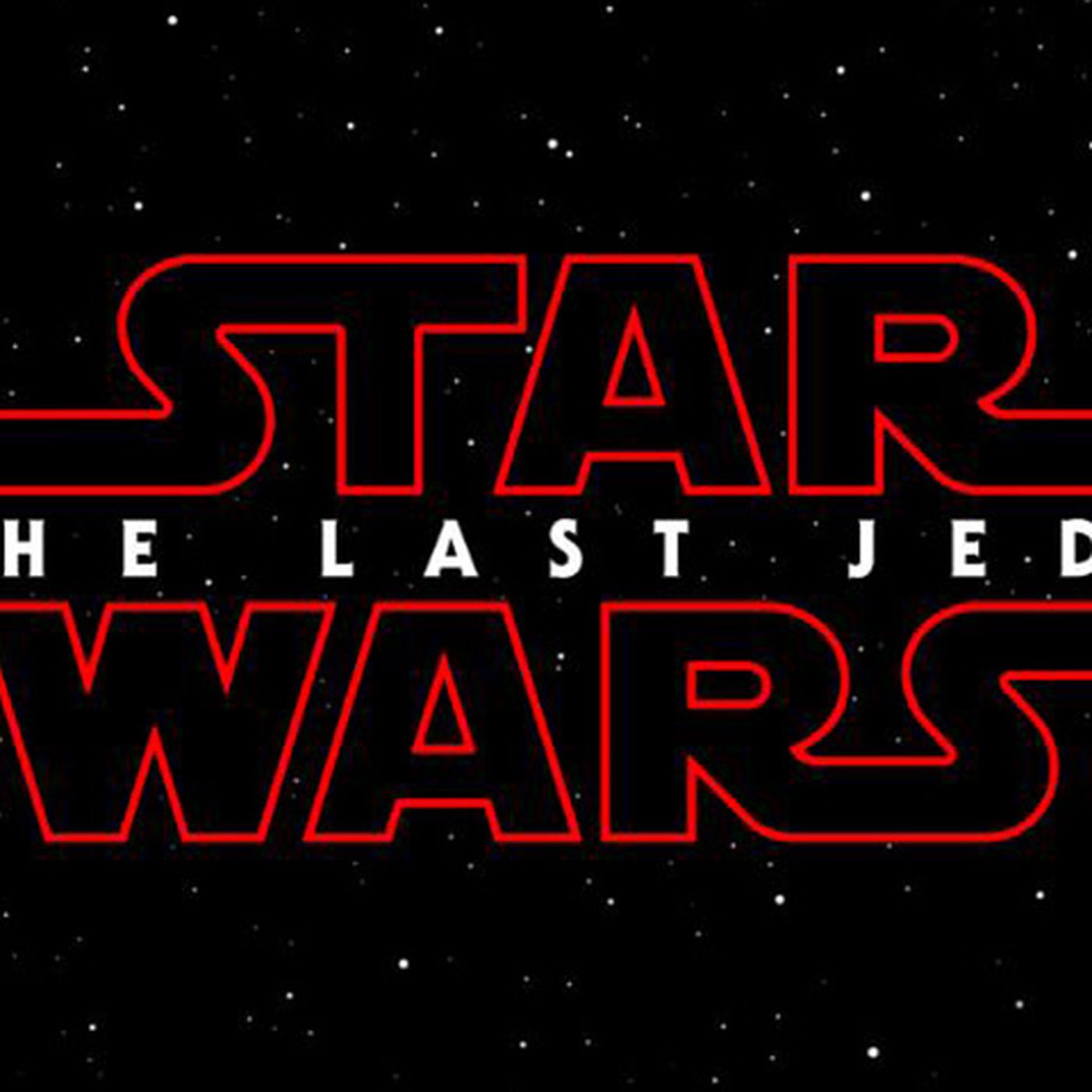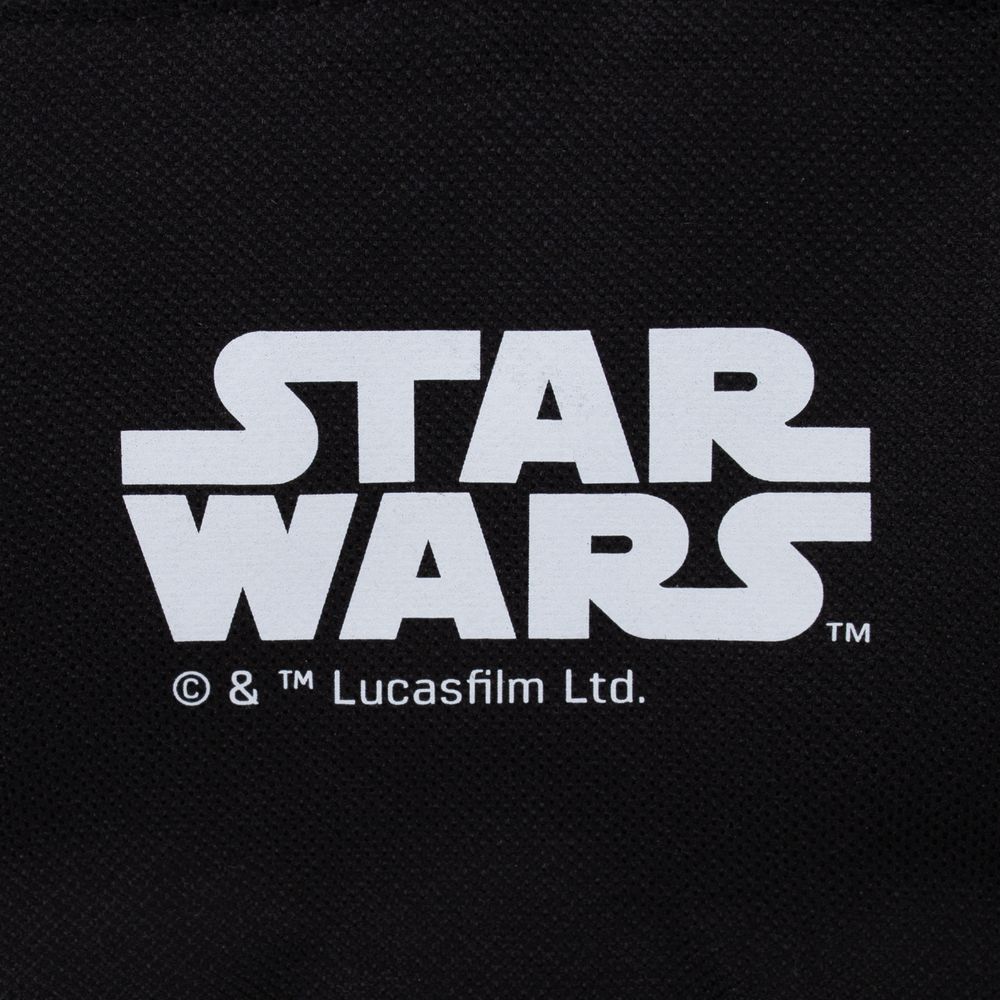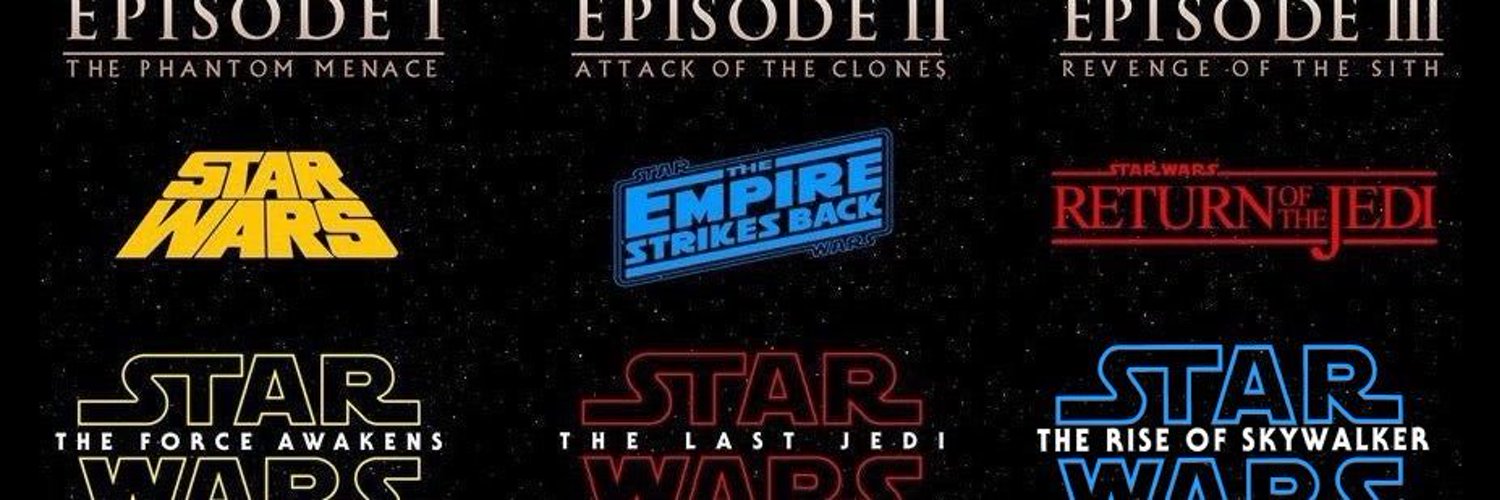
Звездные Войны Update: Новый шрифт, подкорректирован шаблон. Новый формат дат. (До битвы на явине) (после б.я) Империя Хатт Хатты — раса больших брюхоногих, которым присущи маленькие руки, широкий рот и огромные глаза. Они контролировали гигантскую космическую империю в Пространстве Хаттов. Хатты произошли с планеты Варл, но затем перебрались на Нал Хатту. Стоит что многие из хаттов были криминальными баронами. Взрослые хатты представляют собой тучных существ с общим весом тела около одной тонны. у хаттов довольно сильное сопротивление к обману разума через Силу благодаря природному иммунитету. Хатты могут видеть в ультрафиолетовом свете и других спектрах, невидимых для человеческого глаза.
Часто богатые хатты подсвечивали свои дворцы в спектрах такого рода, давая злоумышленникам ложное чувство скрытности. 25 тыс. дбя До создания Галактической империи, на внешних кольцах галактики, а так же на некоторых системах средних колец, появилась империя хаттов. Ее правление заняли главные кланы хаттов, называемые Кланами Древних. В период от заката Империи Раката, и до основания Республики, империя хаттов являлась основной и доминирующей силой. Ксим, также известный как Дарита Ксим и Ксим Деспот -человек,мужчина. В 20 лет разбоготел благодаря деньгам награбленным его отцом, Королём Пиратом Зера 8. Империя хаттов заключила союз с никто, клатуинцами и водранами, для битвы за планету Вонтор. После сражения победившие хатты и их союзники подписали Вонторский Договор, устанавливающий господство хаттов, над расами и всем звездным скоплением Си’Клаата, внешнего кольца галактики. После битвы, Ксим был предан, и брошен в тюрьму хаттов, где сгнил так и не увидев свободы.
Со временем Империя Хаттов развалилась, участвуя в постоянных локальных войнах. На рубеже зарождения Республики, агенты поспособствовали уничтожению ключевых фигур Хаттов. Оставшееся пространство после Империи, стало именоваться Пространством Хаттов, где в отдельных регионах правили отдельные кланы Хаттов. Гипердрайв .До времен республики, у многочисленных рас небыло своих гипердвигателей, и заменой служили различные технологические приспособления. У людей это были стазис камеры, позволяющие лететь в течении столетий без старения, или гиперпушки, которые в прямом смысле отстреливали корабли, позволяя им развить скорость равной скорости света, и тем самым образовать гипертунель. Чуть позже, после падения империи Раката, люди стали улучшать свои технологии, и вошли в число первых рас, кто создал собственный гипердвигатель, на основе ракатского. В их число вошли рогатые гуманоиды Деваронцы, с планеты Деварон, и Госсманы, похожих на маленьких динозавров существ, с планеты Кастелл.
Госсман Семена Республики В конце 25 тысячилетия дбя, почти через двести лет после падения империи раката, народы планет Кореллия и Дуро, наконец открыли способы работы с Силой, настроив двигатели раката, и на их основе создали более современную версию гипердрайва. В течении 20 лет, технология была стабилизирована для массового пользования и Коррелианцы стали продавать двигатели в ближайшие звездные системы. Позже и остальыне расы присоеденились к разработкам двигателя, тем самым последующие тысячилетия двигатель изменялся и усовершенствовался в зависимости от потребностей той или иной расы. Это время было названа Эпохой Экспансии. Много новых рас покидало свои родные миры, и отправлялись исследовать новые звезды. Торговые отношения в центральном секторе галактики, зародили первые семена будующей Галактической Республики. зг< Charge planes зз Effect channels 34 Inter-level conduits 35 Core chamber holds generator Пример строения Гипердрайва. Рождение Республики состоялось при подписании Галактической Конституции в 25053 ДБЯ во время Объединительных войн.
В тот период люди и дуросы, изучив технологии Раката, изобрели гипердвигатель, что позволило Корусанту стать столицей Галактической Республики и оставаться ею в течение 25 тысяч лет. Сразу после создания Республики был размечен Перлемианский торговый маршрут, связавший Корусант и Оссус, а также приведший в Республику рыцарей-джедаев. Маршрут сначала соединил Корусант с Оссусом, и корусантцы воссоединились с джедаями,которые покинули Ядро столетия назад и остались там. Развитие Ж Вначале правительство на Корусканте хотело замедлить экспансию. Но вопреки желаниям правительства, кол-во миров вступающих в Республику росло. Этому способствовало желание получить защиту от Хаттов. В 24500 дбя, произошел Первый Великий раскол, причиной тому послужило создание Легионов Леттоу. Раскол Ксендор во время войны с дже’дайи. Первый раскол и последующая война, началась из-за отказа изгнанников ордена, следовать букве закона и подчинятся ордену дже’дайи. Орден предпочитал не придовать им значения, до того, как не были основаны Легионы Леттоу.
Легионами звались ученики и аколиты — изгнанники Каши Мер, а так же отрёкшиеся дже’дайи Ксендора. Ксендор павший джедай, лидер Леттоу, являлся главной древних последователей темной стороны Силы. Он предал учения Ордена, Вместе со своей возлюбленной Арден Лин положил начало Расколу. В резульатет Ксендор был убит в решающей битве, а легион был уничтожен. Арден Лин и Ксендор, основание Легиона. Известно что Ксендор был представителем Каши Мер, изолированного народа с планеты Каши. Будучи чувствительным к силе, он присоединился к Ордену Джедаев. В какой-то период своей жизни, он встретил Арден Лин , которая позже стала его любовницей. Зендор очень интересовался учением Богана и вскоре начал активно использовать его, за что был изгнан из Ордена. Однако некоторые рыцари последовали примеру ксендора, отвергнув учения джедаев и присоединившись к нему. Совет джедаев не оставил этот факт без внимания и вскоре, объявил войну отступникам. В ходе жестокой войны с джедаями, хаос и разрушения устроенные Легионами, коснулись многих планет, включая миры ядра.
Несколько мастеров таких как: Джук-джук Х’брузин, Блендри и Кафаллокс, устав быть «рабами» кодекса и правил, перешли на сторону Ксендора. В итоге Ордену удалось одолеть Легионы Леттоу, окончательно разбив их войска при битве за Колумус. Планета Колумус, является родным домом древней до республиканской расы, под названием Колуми. Колуми считались одной из первых рас-звездопроходцев в Галактике. Разочаровавшись в варварских народах на других мирах, колуми вскоре отказались от космических путешествий и вернулись на Колумус, чтобы развивать собственную расу. Примерное изображение Колуми. История Раката В 24000 ДБЯ Республика вступила в войну с Благородным союзом Десевро и Тиона. Благородный союз Десевро и Тиона — одно из феодальных государств, возникших на руинах Империи Зима через сто лет после его смерти. Столица — планета Десевро. Линия фронта передвигалась в обе стороны по Перлемскому маршруту, и столицы обеих противоборствующих сторон подвергались массированной бомбардировке.
В конце концов победила Республика, настроив хаттов против тионцев. В течение ста лет большая часть Скопления Тион поклялась в верности Корусанту. Исключением стала Десевро, пожелавшая остаться независимой. В последующие тысячелетия был размечен Кореллианский путь, связавший Корусант с Кореллией и мирами за ней. Участок, ограниченный этими двумя маршрутами, стал известен как «Ломоть». С начала использования гиперпространства галактика к западу от Корусанта оставалась аномальной зоной, недоступной для существовавших в Республике технологий, и государство распространялось на восток. Присоединённая часть Ломтя в Центральных Мирах получила название Наконечник Стрелы, а затем Республика распространилась в Колонии. Конфликты В Период Великого Предназначения (20000—17000 ДБЯ) Республика распространилась по Галактике дальше на восток. Несмотря на это, Ломоть оставался центром пригодного для навигации пространства. Наконец, Республика расширилась за северную и южную границы Ломтя, хотя большая часть Галактики оставалась неизвестной, исключая форпосты, вроде Орд-Мантелла (12000 ДБЯ) и Маластара (8000 ДБЯ).
Пространство к западу от Корусанта по-прежнему оставалось неисследованным, поскольку аналогов Перлемианскому торговому маршруту и Кореллианскому пути в этом направлении обнаружить не удалось. Хуже того, достижения ограничились лишь прыжками на один или два световых года через аномальные зоны гиперпространства. В течение этого периода сформировался Регион Экспансии. Однако он сильно пострадал в результате попытки Алсакана перехватить власть над Республикой у Корусанта. В результате с 17000 по 3000 ДБЯ произошло 17 Алсаканских конфликтов. Большинство сражений произошло на территории владений противников в Регионе Экспансии, а не в Центре. Нет необходимости говорить, что Корусант каждый раз побеждал. В этот период также произошел Первый Арканский конфликт. Арканские генетики также начали серию экспериментов над другими разумными расами, среди результатов которых наиболее заметным стало превращение шестируких зексто с Троикена в новую расу, названную квермианцы.В 15500 ДБЯ, после неудачного первого контакта, Корусант был атакован Звёздными драконами (Дуинуогуинский конфликт).
Конфликт был разрешён мирным путем благодаря Верховному канцлеру Филлориану и философу Звёздных драконов Борз’Мат’о, совместно основавшим Университет Корусанта. До 12000 ДБЯ на Корусанте также появился Галактический музей. Второй Раскол В 7003 ДБЯ произошел Второй Великий раскол, когда группа падших джедаев обнаружила способ при помощи Силы влиять на жизненные формы. Это дало старт вековой Столетней тьме, явившей Галактике чудовищных существ, в том числе змееподобных левиафанов, высасывающих жизненную энергию и накапливающих её в пузырях-ловушках на спине. Столетняя тьма также известная, как Второй Великий раскол, была конфликтом, который начался в 7003 ДБЯ и окончился приблизительно до 6900 ДБЯ. Второй Великий раскол начался с образования маленькой секты рыцарей-джедаев, которая начала практиковать более необычное использование Силы, чем было принято до этого. Проникая в суть Силы все глубже и глубже, эти рыцари открыли для себя новую невероятную истину. Потоки Силы достаточной мощности могут изменять саму жизнь. С новыми способностями эти джедаи начали ставить эксперименты над другими жизненными формами, по своей воле создавая из них новые виды животных. Было провозглашено, что новая мощь может даже быть использована для победы над смертью и оживления мертвых миров. Другие джедаи относились к этим новым способностям с подозрением, полагая, что такие эксперименты могут привести только к злоупотреблению жизнью. Первые восставшие, Легионы Леттоу, были побеждены и уничтожены в Первом Великом расколе, однако их наследие выжило, и возникла вторая группа диссидентов, ведомая отступниками Аджантой Поллом, КсоКсаан и Карнессом Мууром. Война Отступив из миров, контролируемых джедаями, таких как Тайтон, изгнанники сотворили армию ужасных монстров. Первая форма коррибанских зомби была создана на самых ранних этапах войны. Однако даже несмотря на ужасные воплощения темной стороны джедаи начали теснить изгнанников. Армия монстров была легко побеждена силой Ордена джедаев, но изгнанники отказались сдаваться. Дуэли до смерти между джедаями стали окончанием многих битв этой войны. К началу второй половины этого конфликта тёмные джедаи оказались в безысходности. Их просто превосходили числом, и они не видели пути к победе. Тем не менее они не хотели сдаваться и направили все свои силы и ресурсы на создание самых ужасных монстров тёмной стороны из всех, доселе существующих. При помощи этих леденящих душу созданий, таких как левиафан, армии тёмных джедаев укрепились. Вражеские войска трепетали от способности левиафанов высасывать жизненную сущность живых существ. Корабль изгнанников вышел из гиперпространства возле не отмеченной на картах планеты. Приземлившись на поверхности, они обнаружили диковинную гуманоидную расу аборигенов, которые называли себя ситами. Правящий король ситов — Сит’ари — был шокирован появлением пришельцев, но лицезрев воочию их невероятные силы и развитые технологии, король принял их в своем мире. Но даже несмотря на все усилия совместными действиями джедаи снова оттеснили изгнанников назад. Последние сражение между светлыми и тёмными произошло на планете Корбос. Ближний бой, наряду с бомбардировкой джедаев и Республики, привёл к сдаче последних из тёмных джедаев. После поражения на Корбосе выжившие отступники были окружены войсками Республики. Многие республиканцы требовали публичной казни, но лидеры джедаев настояли на том, чтобы отступников изгнали за пределы Республики, в неизведанные регионы, в надежде на то, что, со временем, они увидят ошибки в своём пути. Их погрузили на одинокий, невооруженный и лишенный брони корабль и отправили в космос. Несколько кораблей должны были проводить изгнанников до границ пространства Республики и убедиться в том, что они его покинут и не вернутся. Столетняя тьма завершились, а Орден джедаев пережил Второй Великий раскол. Новый мир К сожалению, это привело к скорому падению правителя. Теневая рука — его ближайший соратник и второе лицо в правящей иерархии ситов -сговорился с пришельцами и предал своего повелителя. Используя свои умения Силы, изгнанники продемонстрировали полудиким аборигенам поразительные чудеса и провозгласили себя богоподобными правителями Коррибана. Самый сильный из отступников, Аджанта Полл, стал первым Тёмным лордом ситов. Шли годы, падшие джедаи постепенно скрещивались с аборигенами, и вскоре сам термин «ситы» стал означать не только коренных жителей Коррибана, но также их повелителей. Современем аборигены научились использовать знания принесенные падшими, и стали строить храмы. Так была создана Долина Тёмных лордов. Империя Сит В 5000 ДБЯ джедаи республики и империя ситов столкнулись в новом конфликте. Великая гиперпространственная война столкновение между почти забытыми ныне правителями Империи ситов и ни о чем не подозревавшей Галактической Республикой. Конфликт потряс всю Галактическую Республику, несмотря на то, что основные сражения прошли на трех центральных мирах древней Республики, а впоследствии переместились к отдалённой звёздной системе Праймус Голууд и кладбищу ситов Коррибану. Галактическая Республика, преодолев начальный натиск ситского вторжения, перегруппировала свою космическую армаду и уничтожила Империю ситов, вынудив Тёмного лорда Нагу Садоу скрыться на лесистой четвёртой луне газового гиганта Явина. Битва добра со злом, совпавшая по времени с периодом расцвета Старой Республики, определила судьбу галактической цивилизации на тысячи лет вперед. Я надеюсь вам понравился этот пост. Читайте в продолжении: Гиперпространственная война, наследие небожителей, потрясения республики, приход Ревана и Малака. Если у кого есть желание помочь, можете писать: wrkhard@yandex.ru Спасибо за прочтение!
Я попытался подражать оригинальному слогану, насколько это было возможно, используя шрифт ITC Serif Regular с отрицательным отслеживанием -75 для этого типичного для 70-х «узкого, но не трогательного» вида. Я применил отрицательный кернинг -125, чтобы аккуратно спрятать многоточие под плечом «y», и добавил +35 к правой стороне «t», чтобы отделить его от «i». Тем не менее, это могло только получить меня так далеко.Несколько символов отличаются: семейство Elsner+Flake — единственное, у которого правильная буква «t» с хвостиком, но ни в одной цифровой версии нет ни двухэтажной буквы «a», ни буквы «e» с наклонной перекладиной, ни буквы «f». ‘ с удлиненным хвостом. Поскольку большинство шрифтов ITC той эпохи были экранными, они были украшены множеством альтернативных глифов для максимальной универсальности. Это позволило дизайнерам точно настроить блокировку, пока она не стала идеальной. К сожалению, почти ни одно из этих дополнений не попало в цифру. Пришло время кому-то пересмотреть классику рекламы ITC и восстановить ее первоначальную славу.